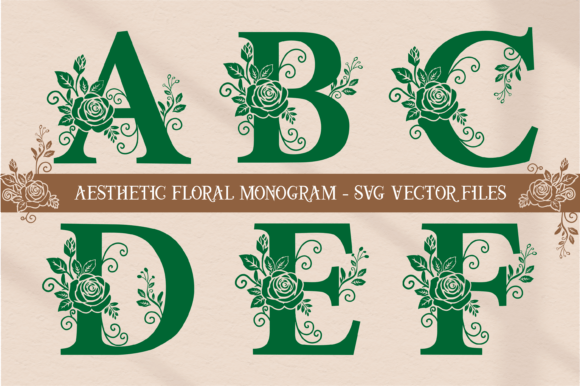
Elegant Floral Monogram SVG Alphabet
適切なデザイン要素を見つけるのは難しい場合がありますが、Elegant Floral Monogram SVG Alphabetは作品を即座に引き立てる優れたコレクションを提供します。
POD(オンデマンド印刷)製品、結婚式の招待状、またはソーシャルメディアのグラフィックを作成している場合でも、Elegant Floral Monogram SVG Alphabetは理想的です。